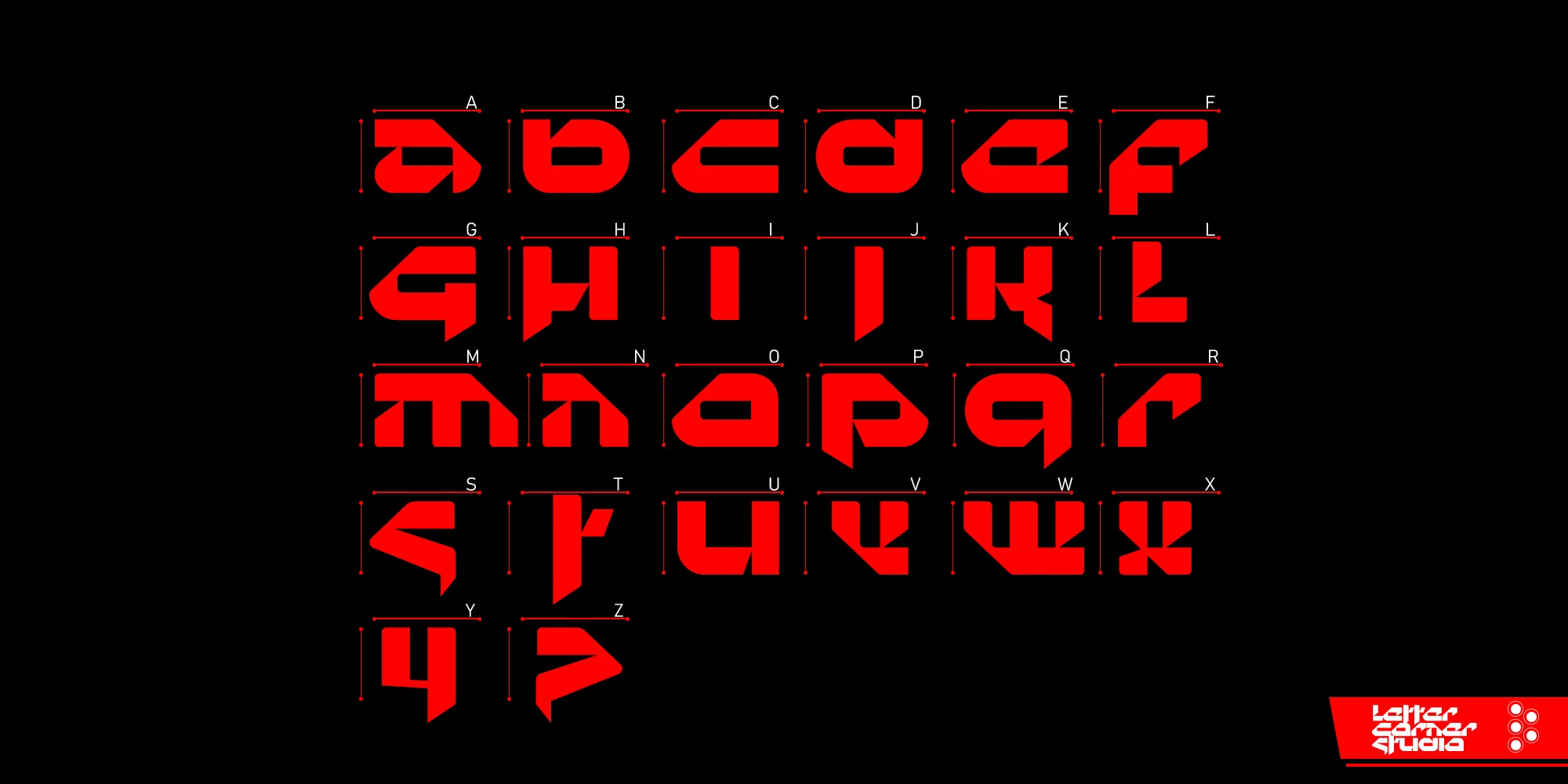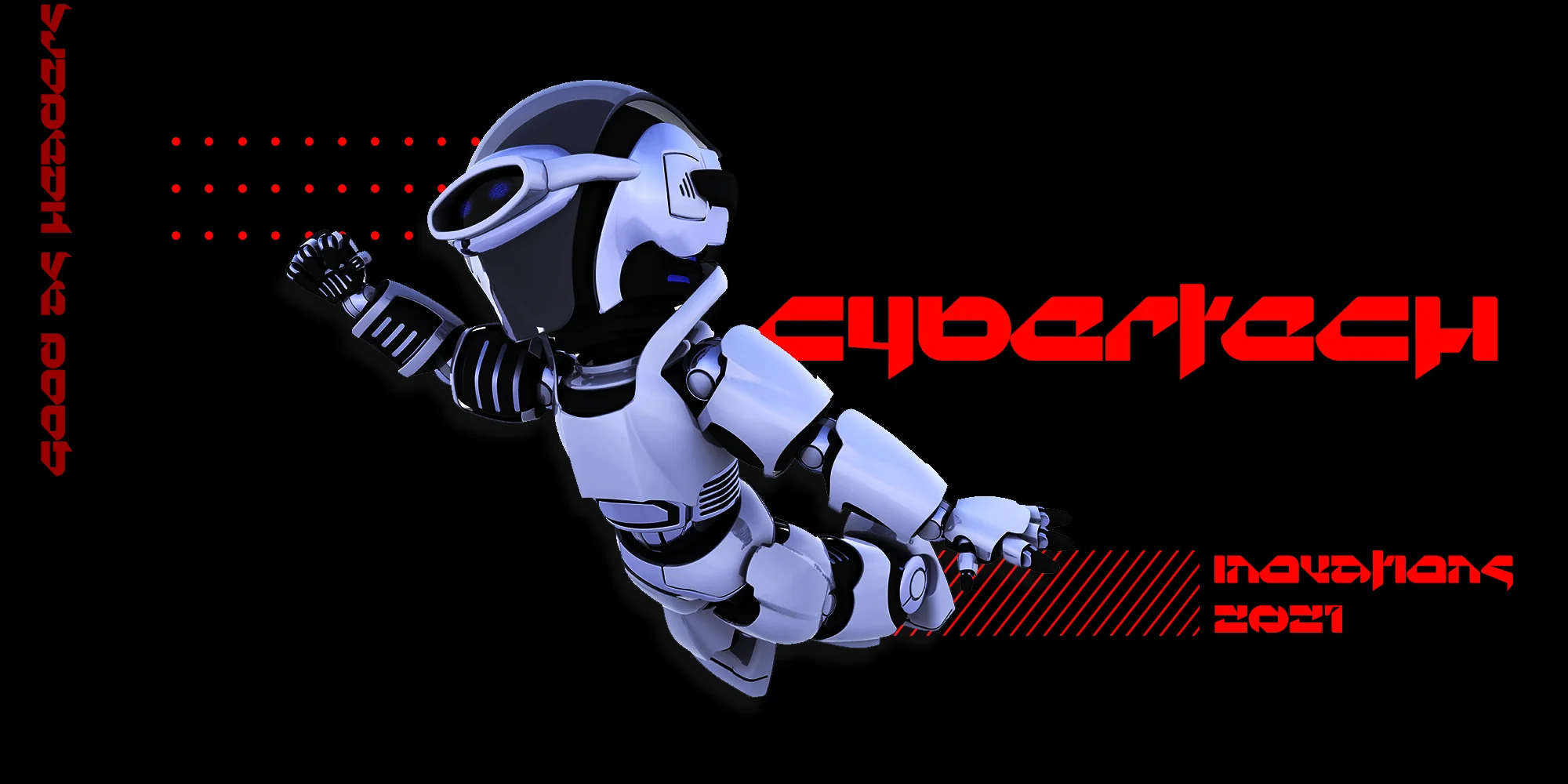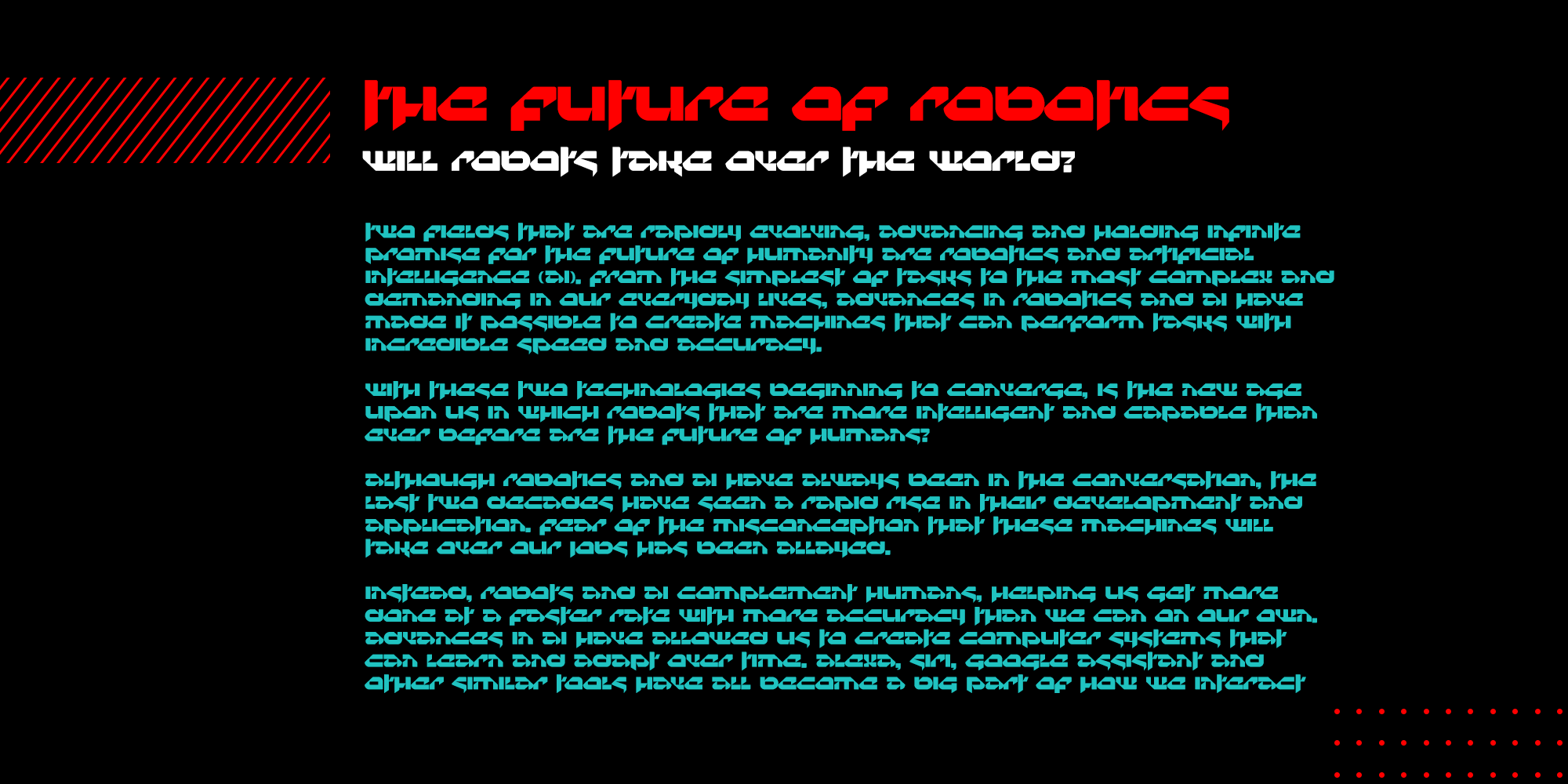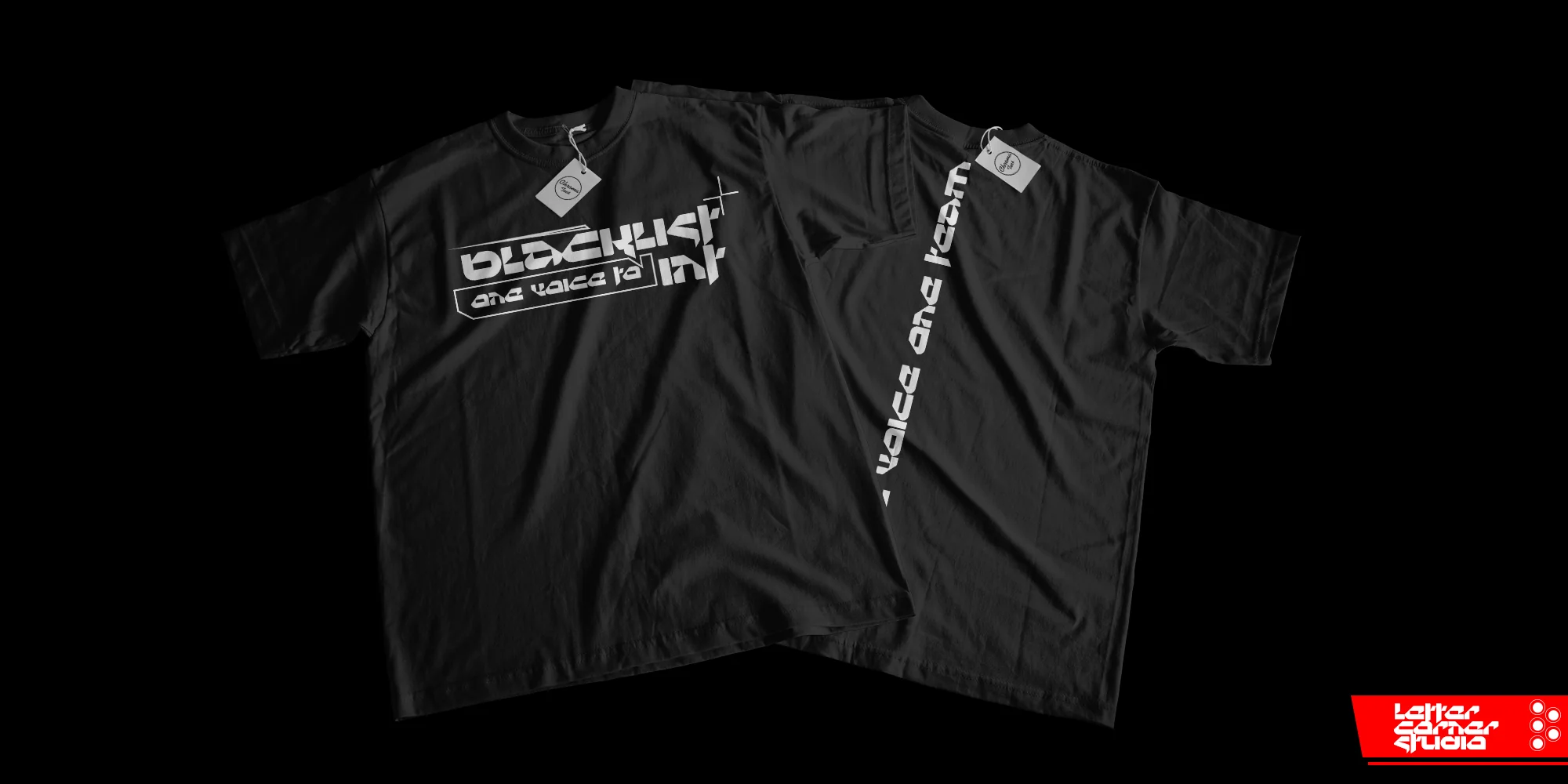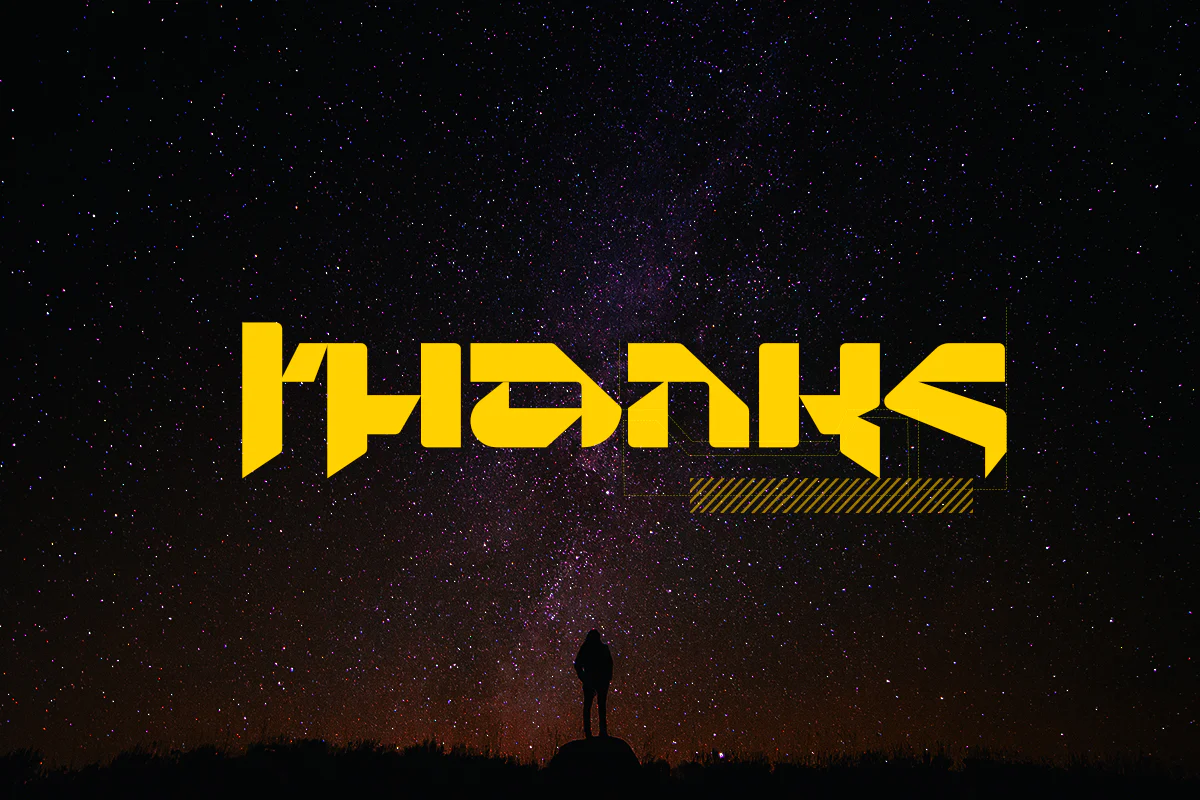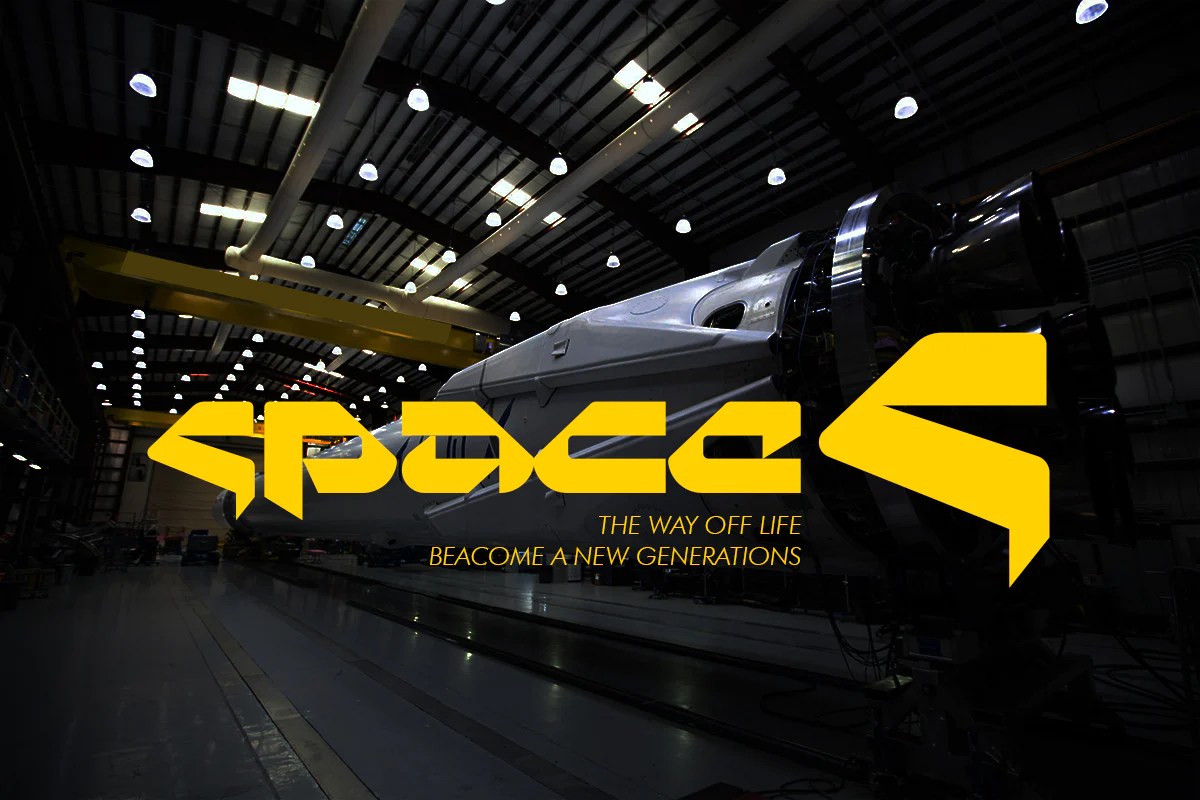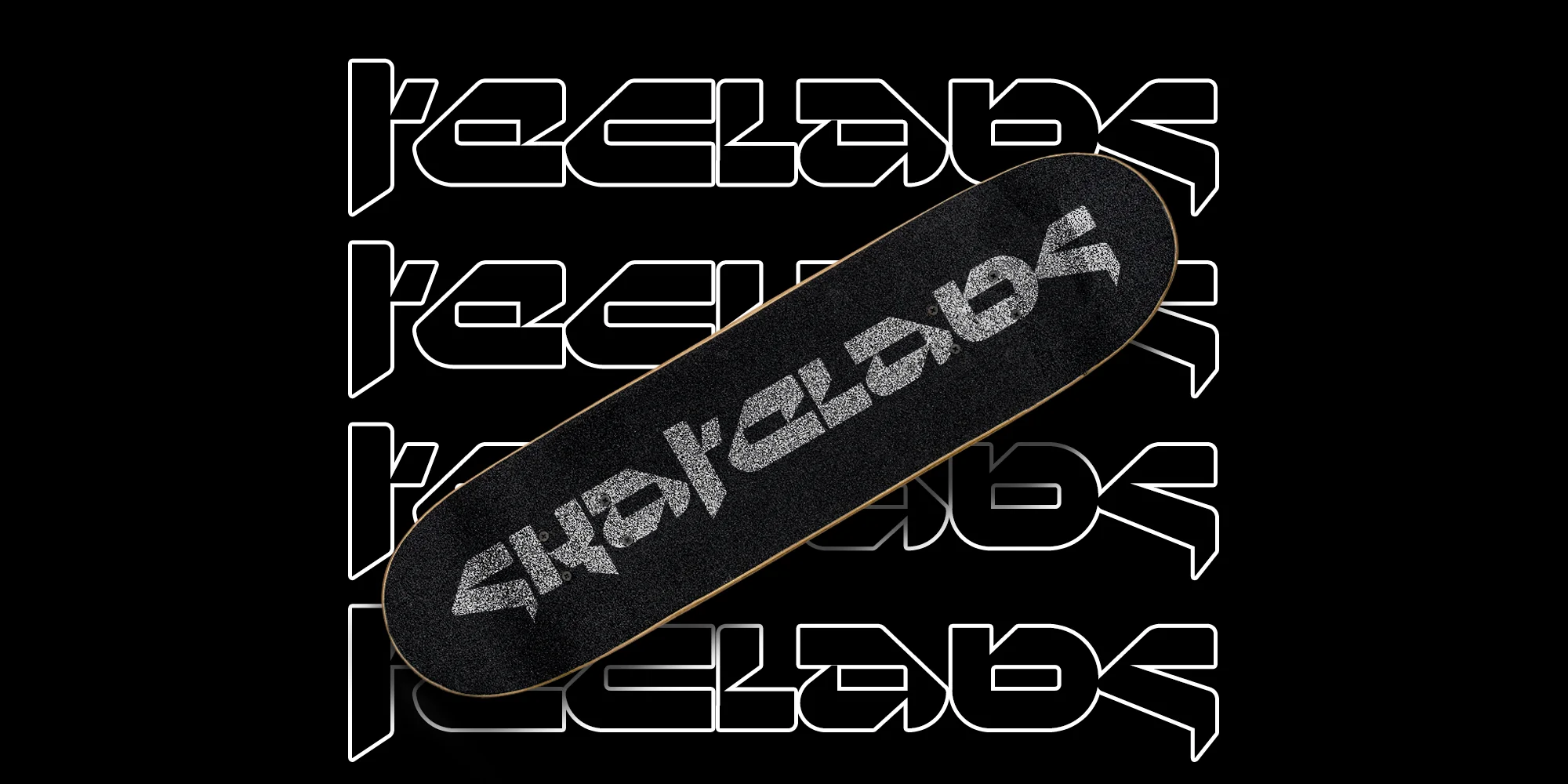
Giới thiệu Techla , một phông chữ hiển thị tương lai và độc đáo. Các dạng chữ kỳ quặc làm cho phông chữ này trở nên hoàn hảo cho việc xây dựng thương hiệu, dòng tiêu đề, biểu trưng, nhãn dán, thiết kế biên tập, v.v.